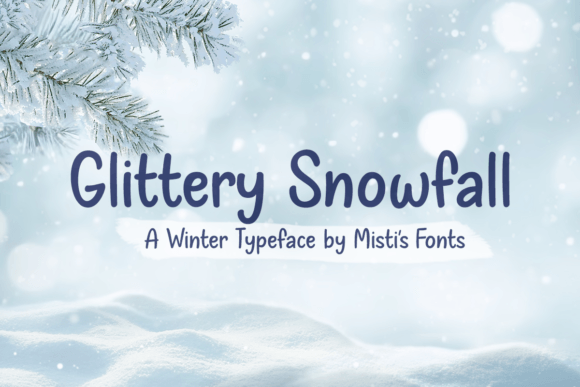
Glittery Snowfall
適切なデザイン要素を見つけるのは難しい場合がありますが、Glittery Snowfallは作品を即座に引き立てる優れたコレクションを提供します。
POD(オンデマンド印刷)製品、結婚式の招待状、またはソーシャルメディアのグラフィックを作成している場合でも、Glittery Snowfallは理想的です。